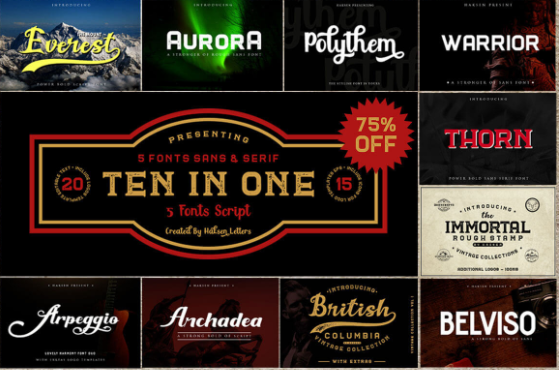
Эта впечатляющая коллекция включает в себя широкий спектр элементов дизайна, которые помогут вам создать идеальный винтажный и стильный дизайн. Набор из 10 уникальных шрифтов состоит из 5 шрифтов без засечек и засечек, а также из 5 шрифтов сценариев. Они имеют ряд дополнительных функций от многоязычной поддержки до альтернатив. Вы также получите 20 настраиваемых шаблонов логотипов и 15 винтажных иконок для добавления в свою коллекцию.
Особенности:
- 10 профессиональных шрифтов - 5 Sans & Serif, 5 скриптов.
- 20 настраиваемых шаблонов логотипов.
- 15 иконок, чтобы оживить ваш дизайн.
- Многоязычная поддержка всех шрифтов.